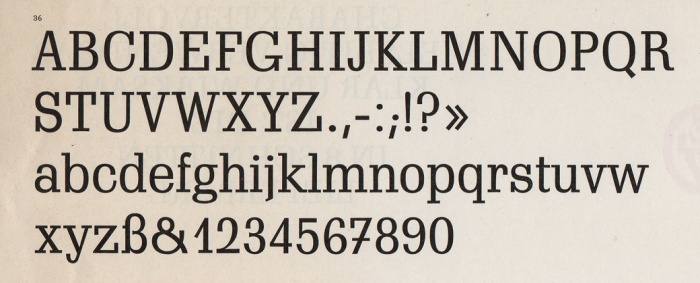
Bleisatzschriften, die es nicht digital gibt
Wäre es sinnvoll, hier mal das Thema "Bleisatzschriften, die es nicht digital gibt" anzuschneiden? Ich weiß zwar nicht, in welche Untergruppe das einsortiert werden sollt (Talk? Geschichte? Veröffentlichungen?), will aber erklären, was ich mir davon verspreche. Also: Ich arbeite noch recht viel mit Blei, entwerfe aber vieles am Computer. Dabei ärgert mich immer wieder, dass es trotz zigzehntausender Fonts noch immer von erstaunlich vielen Bleisatzschriften keine digitalen Ausgaben oder wenigstens Neu-Interpretationen gibt. Es kann natürlich auch sein, dass es die eine oder andere doch digital gibt, ich sie aber nicht finde oder sie nicht käuflich zu erwerben ist. Und da ja hier auch hoffentlich Schriftentwerfer reinschauen, könnte dieser Thread möglicherweise eine Fundgrube für sie werden, auf welche Schriften es sich noch zu stürzen lohnen könnte. Und weil ich ja obendrein nicht der einzige Bleisatzfan hier bin, gibt es doch sicher eine ganze Menge Anregungen. Vielleicht könnte man in irgendeiner Form so eine Art Liste führen, was von diesen angeführten Schriften (vielleicht aufgrund dieser Anregung) von wem digitalisiert wurde oder wird? Hat jemand ne Idee dazu?
Wäre das vielleicht was für das Globaltypeprojekt - eine Verlinkung von Bleisatzschriften und deren digitalen Entsprechungen?
Ich will auch gleich mal den Anfang versuchen und liste hier mal nur ein paar Schriften auf, deren digitale Existenz ich immer wieder schmerzlich vermisse, die mir spontan einfallen und von denen ich glaube, dass man sie auch heute noch bzw. wieder gut verwenden könnte:
1. Typoartschriften:
1.1. "Leipziger Antiqua" - wurde mal (bei Typoart selber vermutlich) digitalisiert, ist m.E. aber nirgendwo legal erhältlich.
1.2. Die "Thannhaeuser-Antiqua" - gabs nur als Handsatzschrift in mager, kursiv, halbfett - m.W. nie digital, was ich sehr schade finde, weil sie eine gute Alternative beispielsweise zur Optima wäre ...
1.3. Die legendäre "Freundschaftsantiqua" eines chinesischen Kapr-Schülers, steht m.W. exklusiv in der Bleisetzerei der Leipziger Hochschule - weiß nicht ob man sie heute vielleicht auch gebrauchen könnte ...
1.4. Die "Liberta", eine pinselgezeichnete Antiqua in mehreren Schnitten, die ich immer noch gern in Blei verwende, gabs auch für die Linotype ...
2. Bleisatzklassiker
2.1. Ganz weit in Blei vor allem im Norden war die "Genzsch-Antiqua" verbreitet, in vielen Schnitten ...
Eine Hamburgerin hatte m.W. mal in Zusammenarbeit mit einer Hamburger Kunsthochschule (oder Fachschule?) den normalen Schnitt digitalisiert. Diese Schrift kam meines Wissens nie in den öffentlichen Verkauf ...
2.2. Von der "Tiemann" gibt es zwar bei Linotype zwei Schnitte, aber keine Kursive ...
2.3. Die "Bernhard-Antiqua" ... vom großen Lucian! ... eigentlich seine schönste Schrift ... unbegreiflich
2.4. Nur was für Liebhaber: Die "Ohio-Kraft", eine deutsche fette Werbekreation der Gebrüder Butter basierend auf der amerikanischen Pabst, die es nur in "normal" und kursiv in Blei und digital auch in Caps gab bzw. gibt.
2. 5. Die holländischen Bleisatzklassiker "Romanee" und "Romulus", beides m.W. Monotypeschriften, scheint es (zumindest unter ihrem eigenen Namen) nicht zu geben. Von der einen wird ja sogar behauptet, dass es die erste Schriftsippe hätte werden sollen und können, wenn man van Krimpens angeblich fertigen Zeichnungen der Sans gegossen hätte - mindestens 30 Jahre vor der Erfindung des Begriffs "Schriftsippe" ...
Eine Hamburgerin hatte m.W. mal in Zusammenarbeit mit einer Hamburger Kunsthochschule (oder Fachschule?) den normalen Schnitt digitalisiert. Diese Schrift kam meines Wissens nie in den öffentlichen Verkauf ...
Ich würde mal vermuten, dass das an der HAW Hamburg, Fachbereich Gestaltung passiert ist, da diese über einen hervorragenden Typografiebereich verfügt und – wie an anderer Stelle bereits erwähnt – die Bleisatzwerkstatt. Da wäre dann vermutlich Professor Veljovic der zuständige Prof gewesen. Da könnte man nachfassen.
Halte ich für eine schöne Idee; es gibt da bestimmt einige Klassiker mit der der Welt mehr gedient wäre als mit einer »tollen neuen« Schrift ... :-D
für die Hinweise. Bei der Genzsch hatte ich mich nicht richtig ausgedrückt: Ich selber hab diese Schrift (bin also versorgt), finde es aber schade, dass es nicht mehr Schnitte gibt und die Schrift nicht frei zu kaufen ist. Die Hamburger Kunsthochschule hatte übrigens zumindest bis nach 2000 sogar eine noch größere Bleisatzwerkstatt als die Fachhochschule mit vielen sehr schönen Schriften in unglaublich guten Zustand und hat in den 90ern auch mal ein sehr schönes Schriftmusterbuch daraus gemacht.
Ich bilde mir auch ein, die Genzsch als "Nordische Antiqua" in einer (nicht bleigesetzten) Publikation der Kunsthochschule gesehen zu haben - also kann sie auch dort entstanden sein.
Bei der Bernhard gibts digital eben immer nur diesen einen schmalfetten (?) Schnitt. Viel schöner und vielleicht sogar als Mengentextschrift verwendbar wäre aber der gewöhnliche. In Blei wurden jedenfalls ganze Bücher draus gesetzt. Es gab auch mindestens noch einen kursiven Schnitt in Blei, möglicherweise sogar noch weitere ... Die alle gibt es eben nicht bei MyFonts. Die Belucian, Lucian, Bernhard Schönschrift, Bernhard Modern, Bernhard Fashion etc. haben damit nix zu tun. Am ehesten noch diese eine Kursive von NicksFont, aber auch die scheint mir eher Bernhards Plakaten entlehnt ...
James Felici, der Autor von »The Complete Manual of Typography«, nennt hier zehn Schriften, die es nicht von der bleiernen in die digitale Welt geschafft haben.
Er vermisst eine getreuere Nachbildung von Oldrich Menharts Figural, als es die ITC-Version ist.
Ihm fehlt auch eine digitale Version von Giovanni Mardersteigs Fontana.
Von Jan van Krimpen müssten gleich zwei Schriften digitalisiert werden: Lutetia
und Romulus.